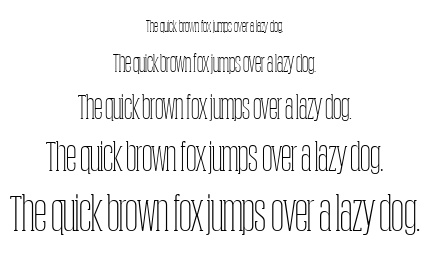
Obcecada Serif es una tipografía geométrica slab serif muy condensada y fina con acabado redondeado en las astas y uniones con ascendentes y descendentes cortos.===========Obcecada Serif is a very condensed geometric fine finish rounded slab serif typeface antlers and joints and falling short.===========• Descarga gratis las versión completa de la fuente desde mi web (497 glyphs)• Letras griegas• Números disponibles en mi web.• Sólo para uso personal.• Licencia comercial disponible + webfont• Download the full version from my website.(497 glyphs)• Greek characters• Numbers available on my website.• Only for personal use.• Commercial license available + webfont===========Full download: Obcecada Serif font 2015